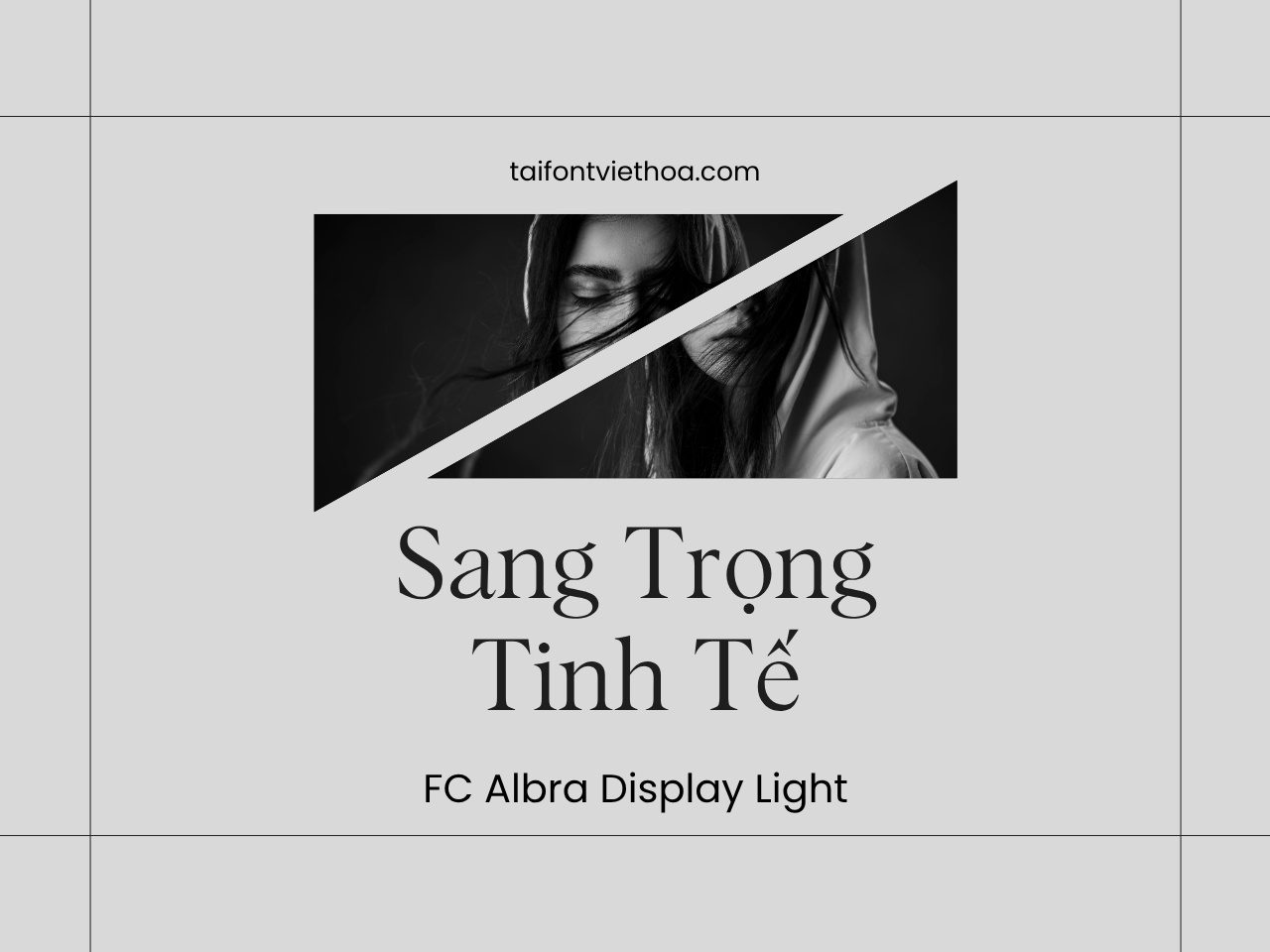
Font việt hóa FC Albra Display Light
Giới thiệu về font Albra Display Light và phiên bản Việt hóa
FC Albra Display Light là phiên bản Việt hóa từ font gốc “Albra Display” – một thành viên thuộc hệ thống chữ cao cấp Albra Typeface, được phát triển bởi CAST (Cooperativa Anonima Servizi Tipografici) – studio thiết kế phông chữ danh tiếng đến từ Ý. Albra Display thuộc nhóm serif hiện đại mang nét cổ điển, được tinh chỉnh chuyên biệt cho các tiêu đề lớn (display) với độ mảnh thanh lịch, giúp tạo nên cảm giác trang nhã, tinh tế và sang trọng. Font gốc hỗ trợ hơn 200 ngôn ngữ nhờ sử dụng bảng Latin mở rộng, và được ứng dụng rộng rãi trong các lĩnh vực như thời trang, nghệ thuật, biên tập cao cấp và thương hiệu cao cấp.
Khác biệt hoàn toàn so với phiên bản “1FTV VIP Albra Display Light” từng được phát hành, FC Albra Display Light là một bản Việt hóa độc lập, được thực hiện bởi cộng đồng Font Chuẩn, với hệ thống dấu tiếng Việt chuẩn Unicode được tinh chỉnh cẩn trọng để giữ trọn vẻ thanh thoát và cân đối của bản gốc.
Đặc điểm thiết kế thanh lịch – Ứng dụng chuyên nghiệp
FC Albra Display Light sở hữu các nét chữ serif truyền thống, với đường nét sắc sảo, thanh mảnh và có độ tương phản cao giữa nét chính và nét phụ. Điều này giúp font nổi bật khi dùng ở kích thước lớn như tiêu đề, bìa sách, poster quảng cáo hoặc các ấn phẩm đậm chất biên tập. Kiểu chữ in hoa được thiết kế đặc biệt để mang lại cảm giác sang trọng, trong khi các chữ thường giữ được sự cân đối và tinh tế.
Font này phù hợp với nhiều ngành nghề yêu cầu tính thẩm mỹ cao như thời trang, mỹ phẩm, thiết kế nội thất, truyền thông cao cấp, tổ chức sự kiện, nhà xuất bản, và cả lĩnh vực bất động sản. FC Albra Display Light còn là lựa chọn lý tưởng cho các thương hiệu nữ tính hoặc sang trọng cần phong cách cổ điển hiện đại pha chút nghệ thuật.